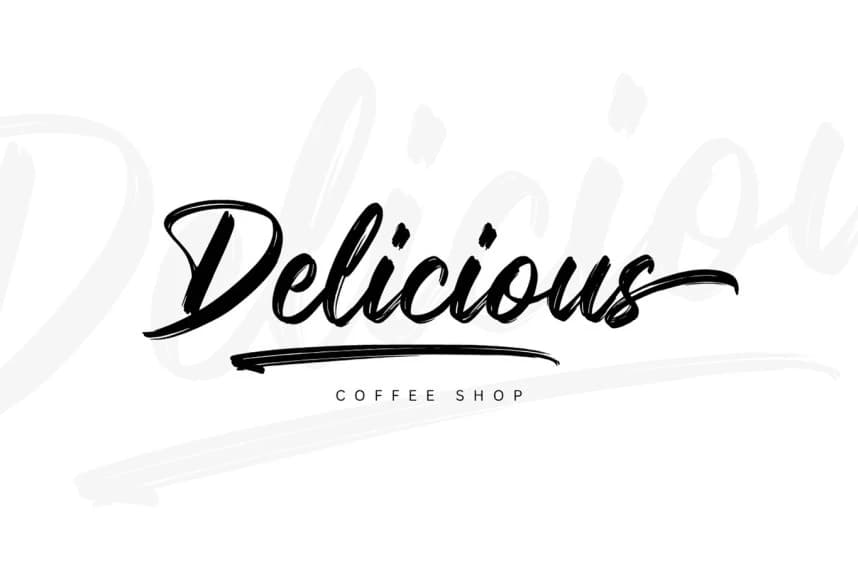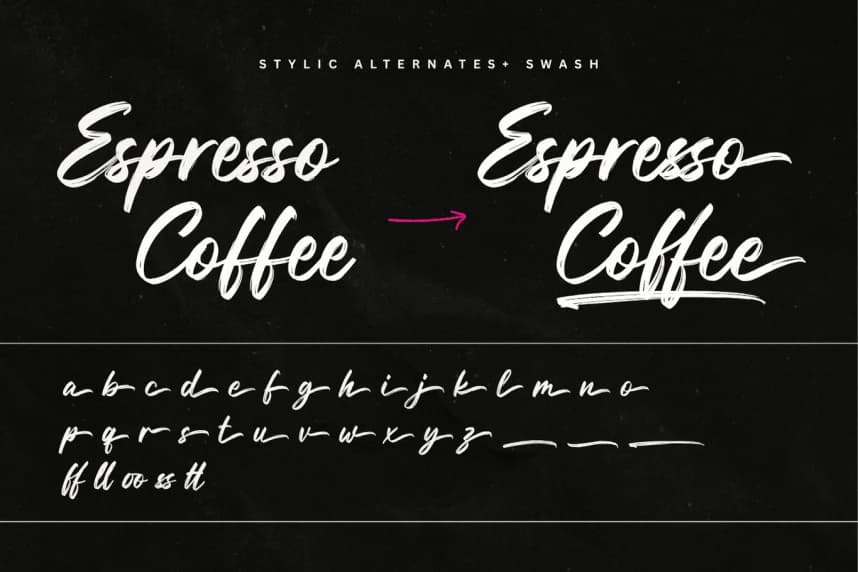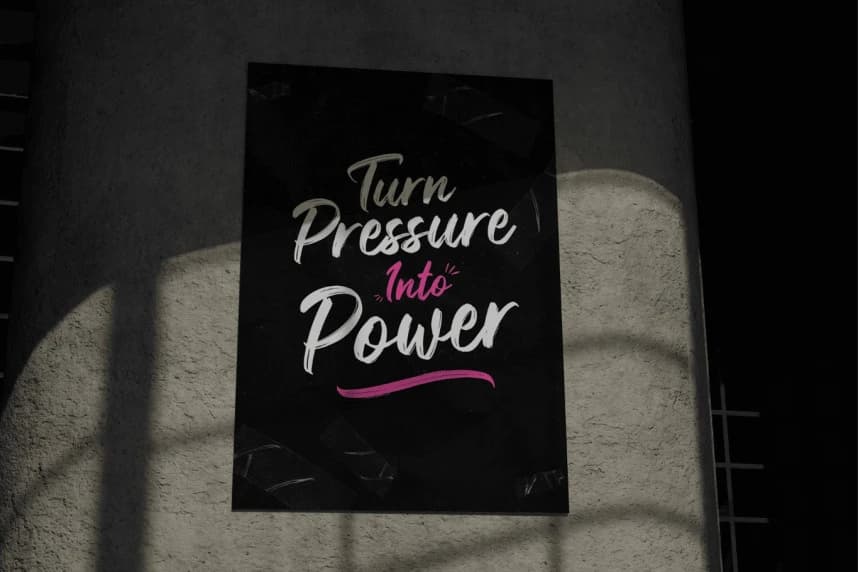
Brush Rings Yazı Tipi
Brush Rings Font, Nirmana Visual tarafından tasarlanmış premium bir el yazısı fontudur. Gerçekçi dokular ve organik vuruşlarla tasarlanmış bu font, gerçek bir boya fırçasının ifade gücünü ve serbestçe akan hareketini kusursuz bir şekilde yakalar.
Brush Rings Font, Nirmana Visual tarafından tasarlanmış premium bir el yazısı fontudur. Gerçekçi dokular ve organik çizgilerle tasarlanmış bu font, gerçek bir boya fırçasının ifade dolu, serbest akışlı hareketini mükemmel bir şekilde yakalar.